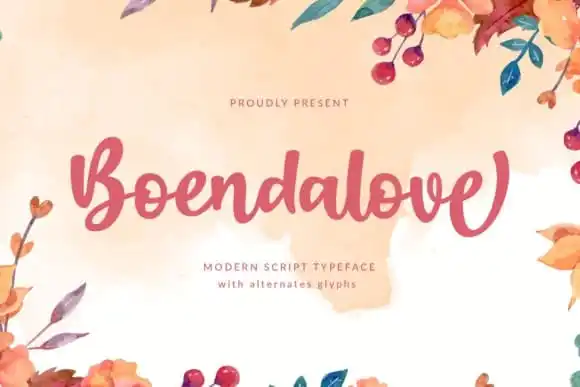
Boendalove Script Font – Download Grátis
A Boendalove Script Font é uma elegante escrita à mão que combina curvas atrativas com um toque urbano fresco, resultando num traçado sofisticado e estilizado. Foi criada pelo designer ahweproject, conhecido por sua habilidade de transformar textos digitais em estilo humano e realista. Esta fonte é perfeita para quem busca uma linguagem delicada e refinada para seus trabalhos gráficos, seja ele para criar cartões de convidado únicos, arte de papelaria incrível ou postagens sociais impactantes. Com um estilo distinto e duradouro, a Boendalove Script Font permite que você crie designs memoráveis e únicos. Sua flexibilidade é imensa, tornando-a uma escolha perfeita para diversas aplicações gráficas, como cartões de aniversário elaborados, trabalhos sociais chamativos ou até mesmo arte customizada para websites. Experimente a Boendalove Script Font e faça sua marca ficar ainda mais marcante e memorável no mundo dos designs digitais.